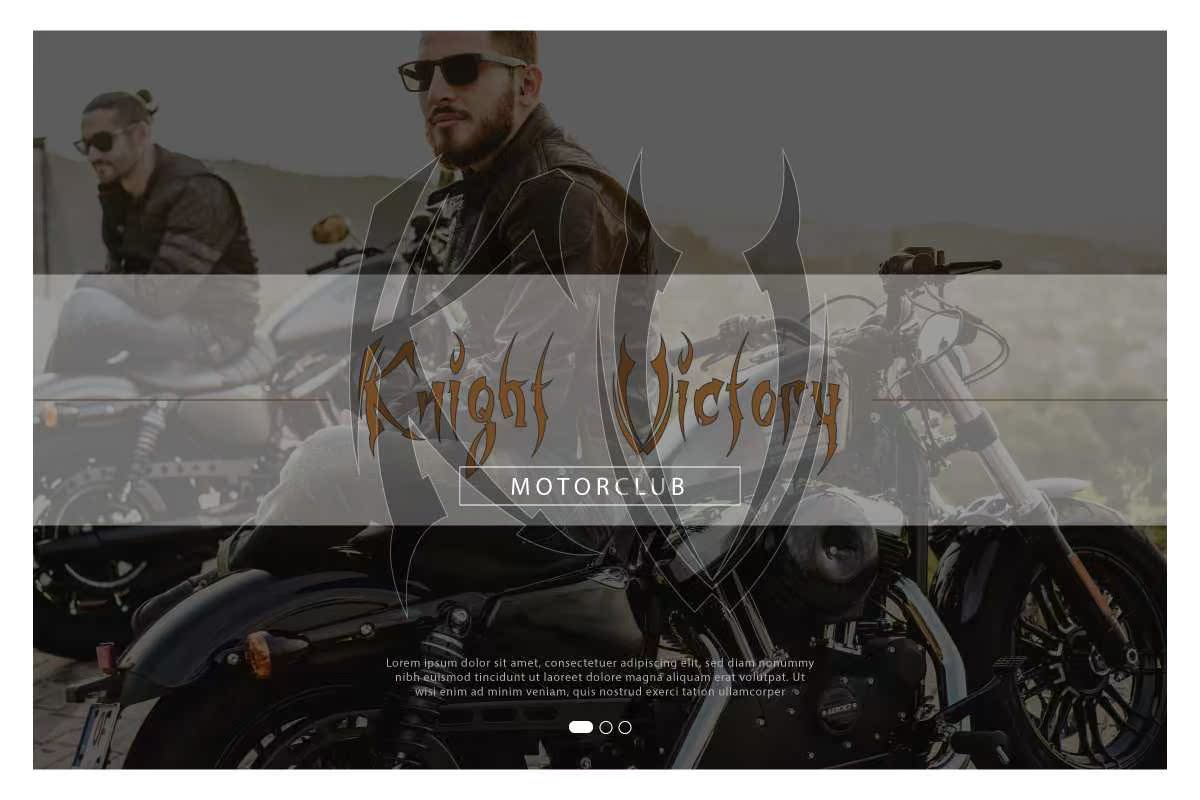
KingFire被燃烧的激情所激发,并将其独特的风格带到每一个设计项目中。这种字体最适合电影、小说的负责人,甚至适合于《摩托车》杂志或《野生动物杂志》。Beitfortheweb,打印或任何时候——King Fireill外观壮观。King Fire被燃烧的激情所激发,并将其独特的风格带到每个设计项目中。这种字体最适合于电影、小说的负责人,甚至适合于《摩托车俱乐部》或《野生生物》杂志的负责人。Beitfortheweb,打印或任何时候——King Fireill外观壮观。